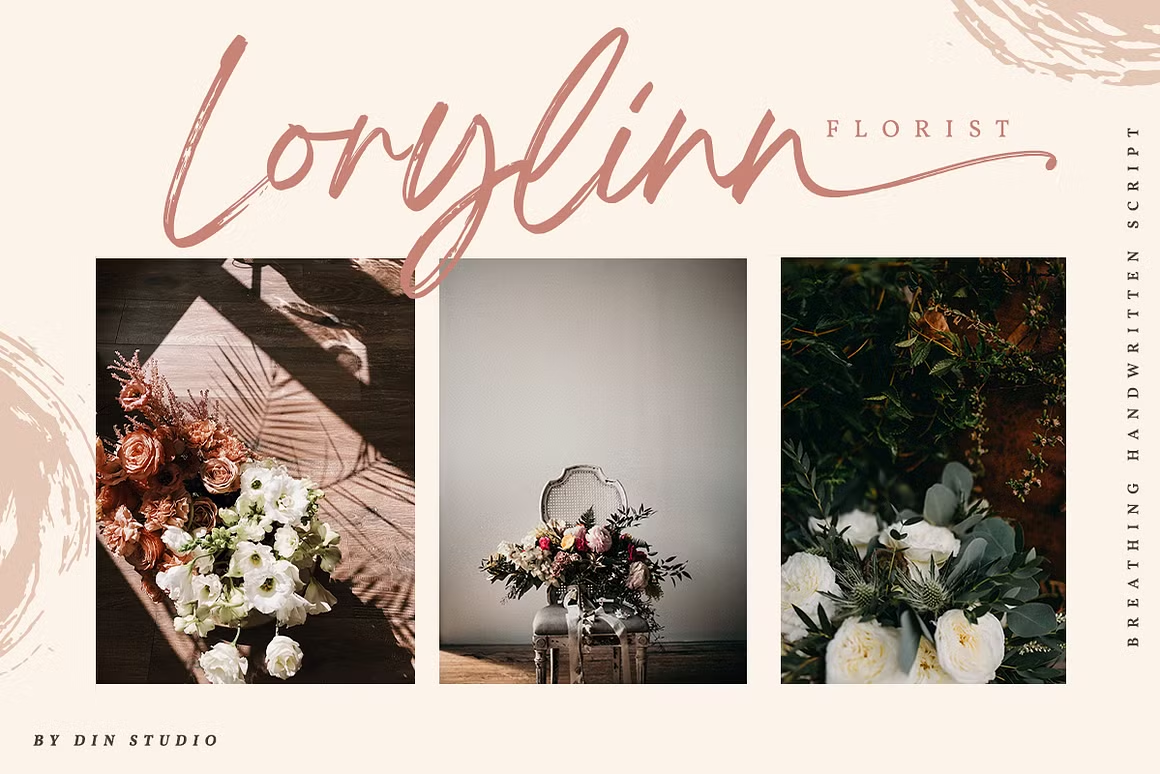
Breathing Font
Breathing Font est une fantastique police de signature au pinceau largement développée pour les emballages de marques de qualité. Chaque lettre a un aspect frais et époustouflant, ce qui augmente le caractère unique et artistique du design. Conçue par notre excellent typographe, Breathing Font est une police multifonctionnelle qui conviendra à diverses applications.
La police Breathing ajoute une touche de style et de classe à toute entreprise grâce à des affiches accrocheuses, des bannières saisissantes, des logos mémorables et de magnifiques couvertures de livres. Ses applications sont infinies : textes, cartes de vœux, vêtements, réseaux sociaux et bien plus encore.
En prévisualisant la police et en explorant ses coups de pinceau, vous pouvez trouver de nouvelles façons créatives de l’appliquer à vos créations. Les coups de pinceau précis et charmants de Breathing Font laisseront une impression durable sur votre public, rendant vos créations plus élégantes et captivantes.
Caractéristiques:
52 Ensemble stylistique
37 ligatures
Prise en charge multilingue
PUA codé
Chiffres et ponctuations